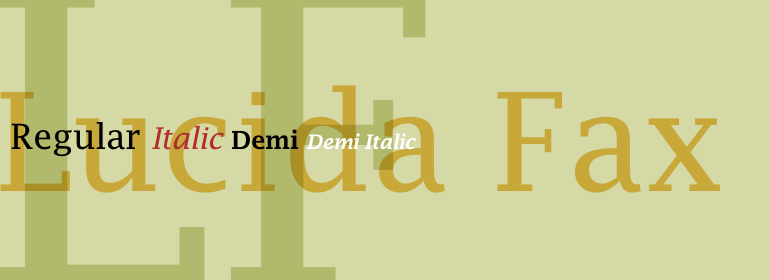
Lucida® Fax
Lucida® Fax,这款字体结构工整、笔画清晰,兼顾美观与易读性,适用于标题、正文、海报、包装、LOGO 等多种场景。字形优雅稳定,风格百搭耐看,适配日常排版与创意设计,让文字呈现更舒适、更具质感。Lucida® Fax一笔一画,皆是细节,以均衡的比例、流畅的线条打造舒适视觉体验,字形端正大气,风格简约现代。无论是商业设计、品牌宣传还是日常排版,都能轻松驾驭,让文字更有格调与力量。Lucida® Fax字体下载。
字体品牌: Monotype 设计师:Holmes,Kris; Bigelow,Charles 字体分类:衬线体 字体属性:外文 字符集:Unicode 发布时间: 2018